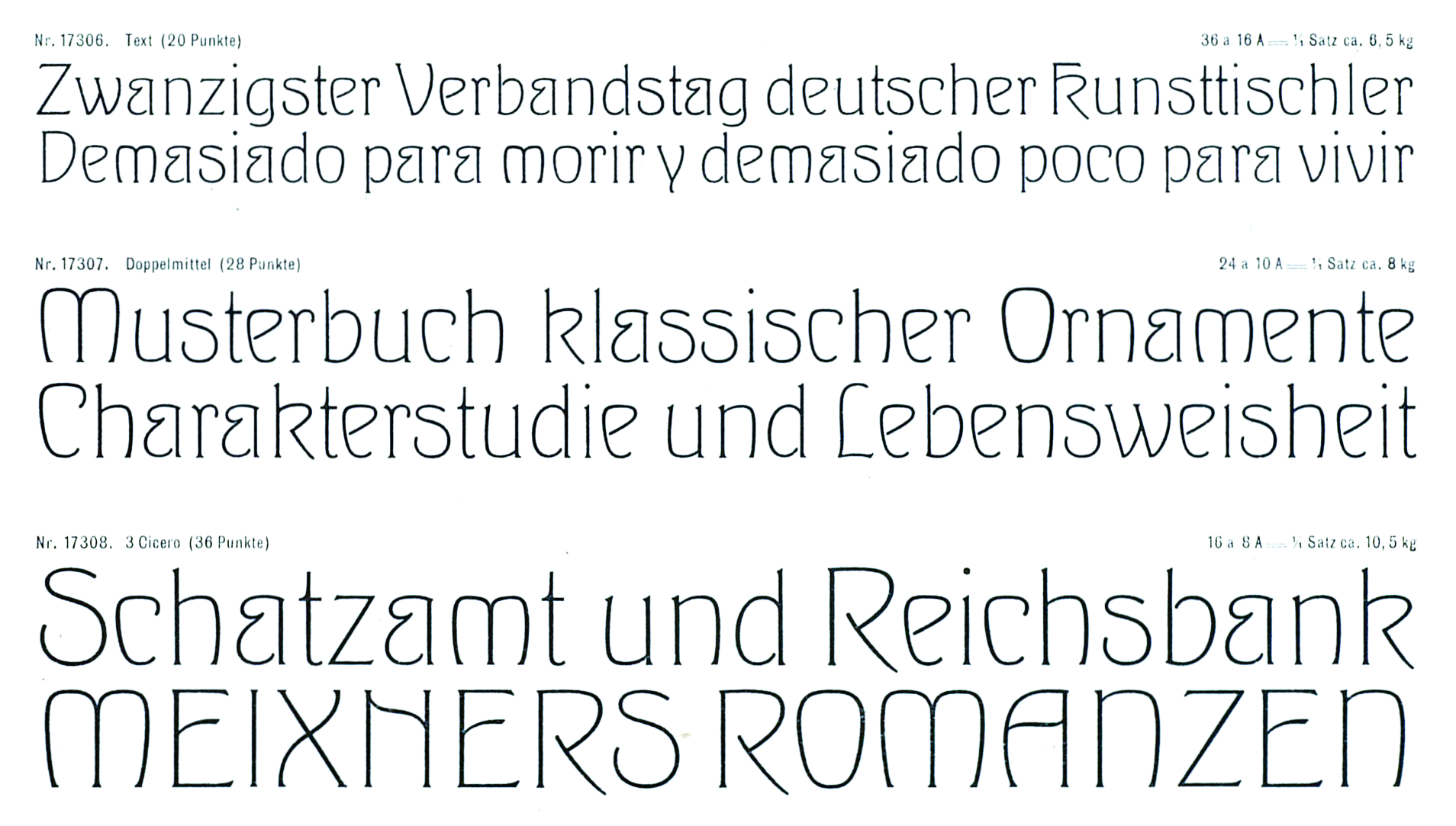
Die Wettin von Heinz Keune erschien 1902 bei Schelter & Giesecke.
Foundry: Schelter & Giesecke Erschienen: 1902 Vertrieb: kein Vertrieb Formprinzip: Antiqua dekorativ Die Wettin von Heinz Keune erschien 1902 bei Schelter & Giesecke. Letter-Library-Schriftmuster Fontlisten mit dieser Schrift Jugendstil-Schriften 1900 bis 1909